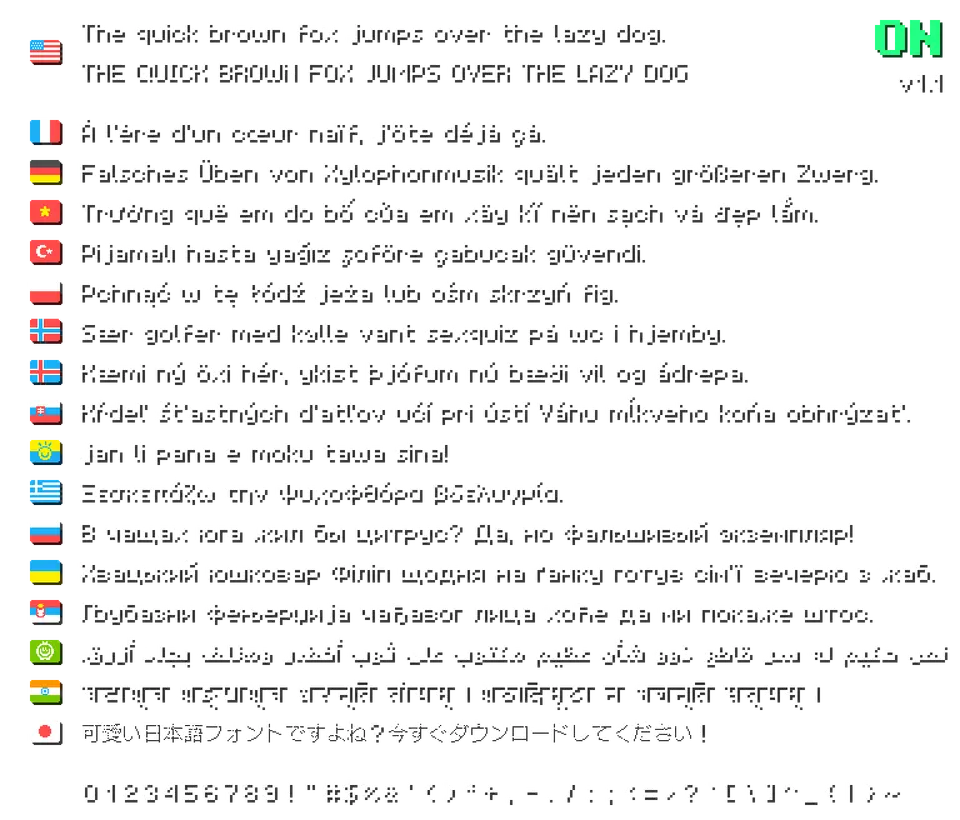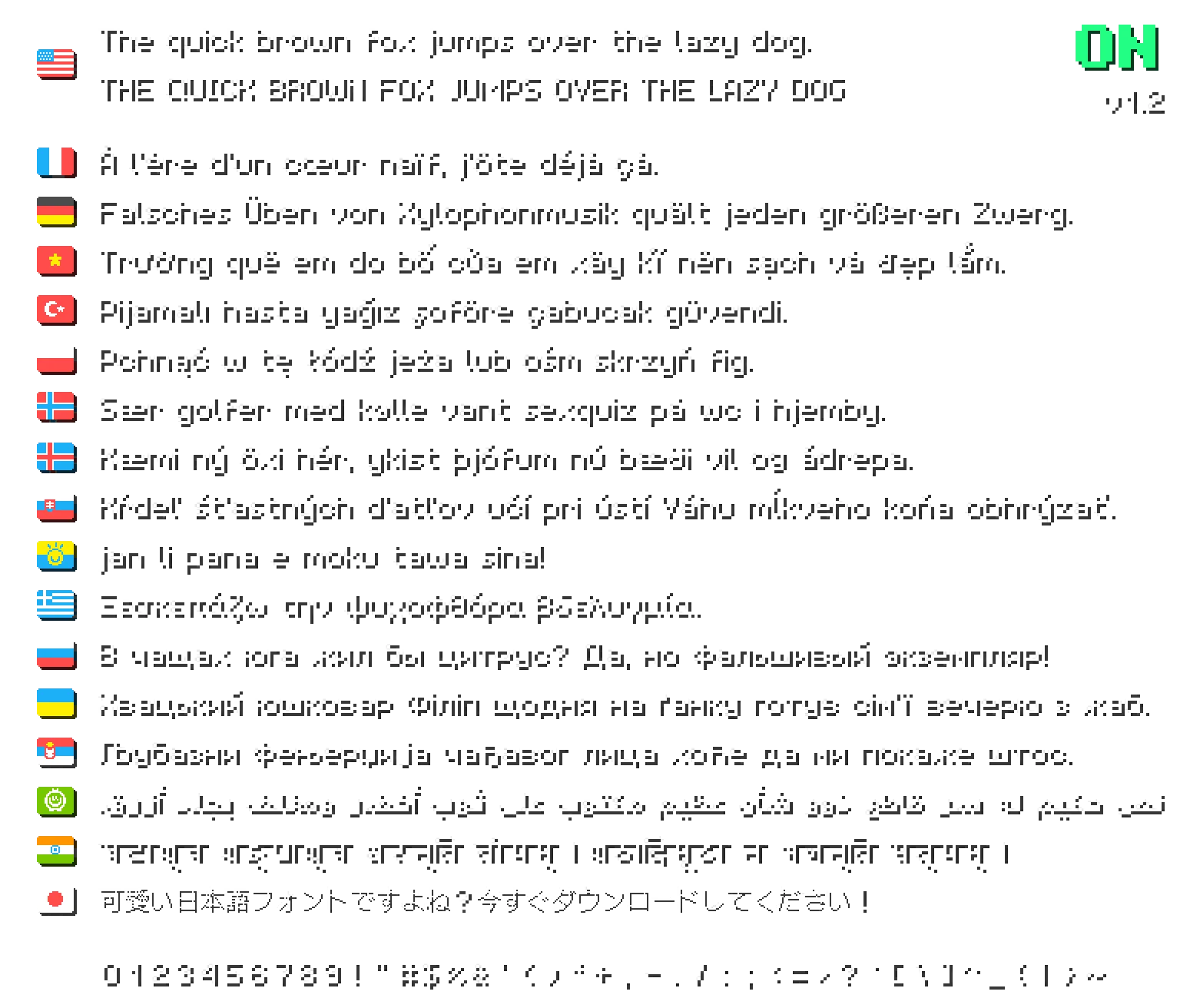
shuriart Font
shuriart Font: что это и зачем нужно​
shuriart Font — это текстурпак, который заменяет стандартный шрифт в игре на более плавный и округлый. Он разработан для улучшения баланса букв и повышения читаемости текста в интерфейсе.
Ключевые возможности​
• Сглаженные и округлые формы символов
• Улучшенная читаемость игровых текстов
• Поддержка латиницы, кириллицы, греческого, арабского, японского и других алфавитов
shuriart Font — качественное решение для тех, кто хочет сделать интерфейс Minecraft более приятным для чтения с поддержкой множества языков.